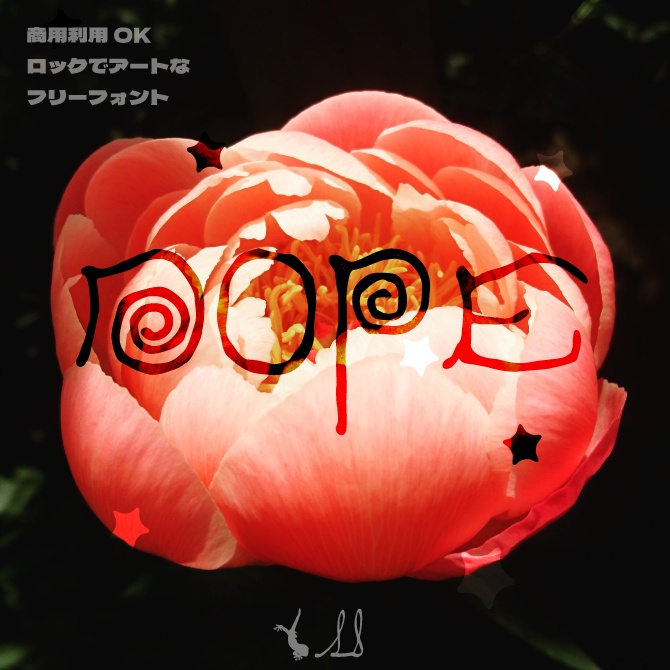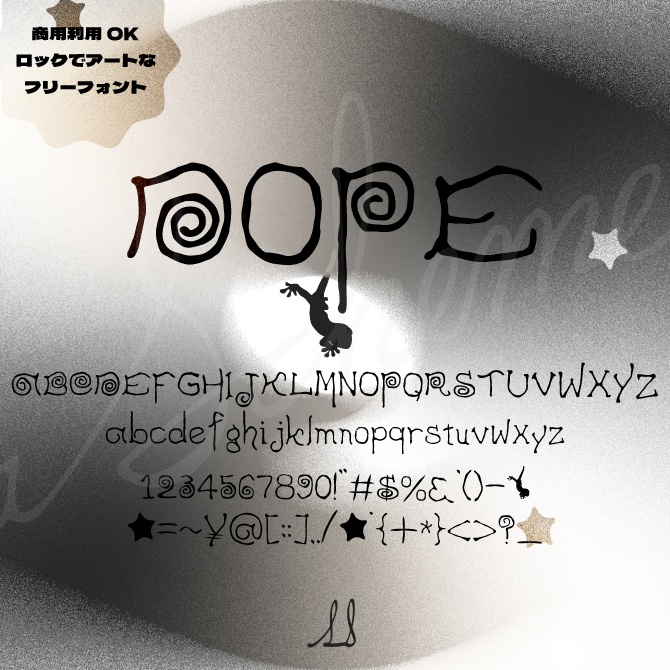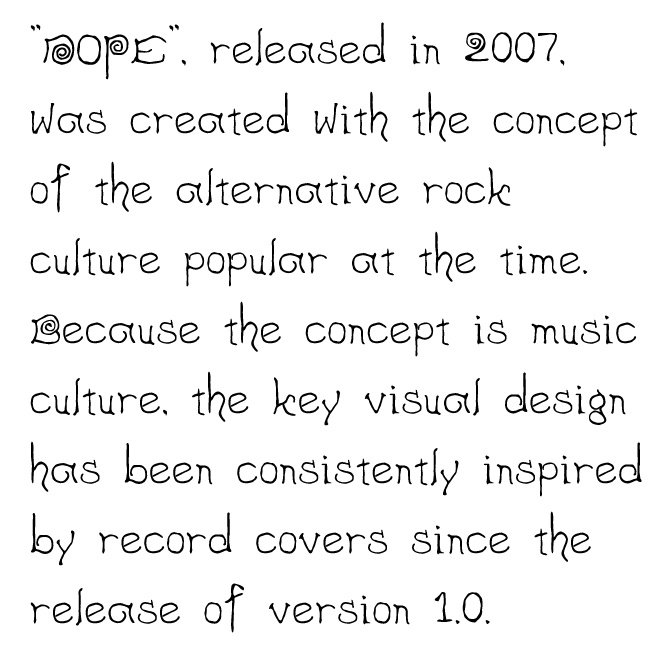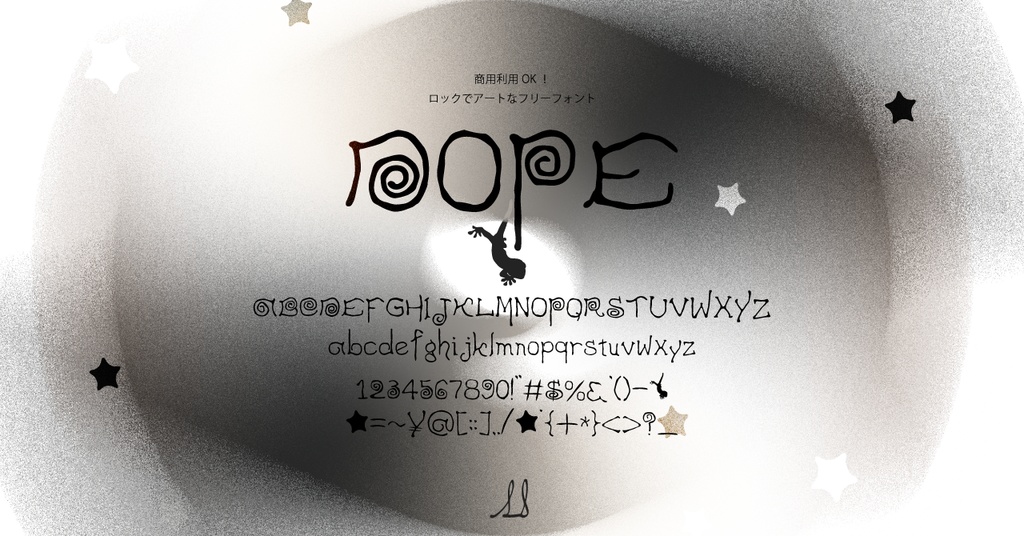
【フリーフォント】DOPE【商用利用OK】
2007年に発表した「DOPE」は当時流行したオルタナティブロックの文化をコンセプトとして制作しました。 音楽文化をコンセプトとしているため、1.0verの発表時からキーヴィジュアルデザインは一貫してレコードのカバーをイメージしたデザインを制作しています。 "DOPE", released in 2007, was created with the concept of the alternative rock culture popular at the time. Because the concept is music culture, the key visual design has been consistently inspired by record covers since the release of version 1.0.